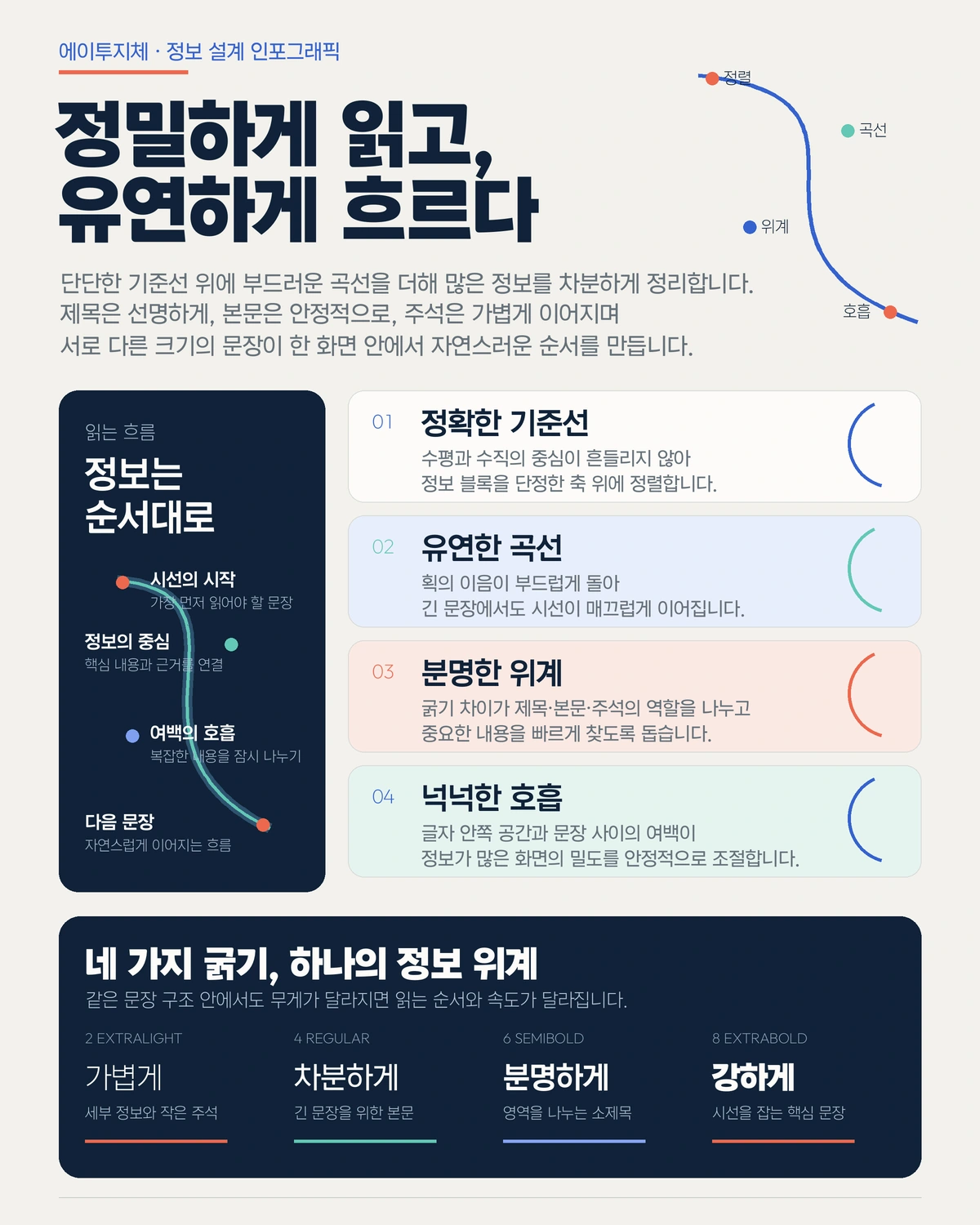
에이투지체 — 오토노머스에이투지X이주임에서 배포하는 무료 폰트입니다. 곡선과 사선이 만들어내는 비대칭적 조화로, 정밀함과 유연함을 함께 담아낸 네모틀 고딕체
자율주행 기업 오토노머스에이투지와 디자이너 이주임이 함께 만든 서체입니다. 한글은 이주임이 직접 설계했고 영문과 숫자는 오픈소스 서체 Outfit을 한글에 맞춰 다듬어 썼습니다.
보도자료가 설명하는 조형의 핵심은 곡선과 사선이 만들어내는 비대칭적 조화입니다. 부드러운 곡선은 도심을 유연하게 주행하는 자율주행의 경험을, 절제된 사선은 앞으로 나아가는 기술적 자부심과 방향성을 나타낸다는 것입니다. 이름의 A2Z는 A부터 Z까지, 곧 처음부터 끝까지라는 뜻이고 슬로건도 처음부터 끝까지 모든 순간을 쓴다는 문장입니다.
굵기는 Thin부터 Black까지 아홉 가지로 본문용 일곱 종과 제목용 두 종으로 나뉩니다. 오픈 폰트 라이선스라 수정과 재배포가 자유롭습니다. 다만 한글이 2,780자로 완성형 전체는 아니어서 드문 음절에서는 글자가 빠질 수 있습니다.